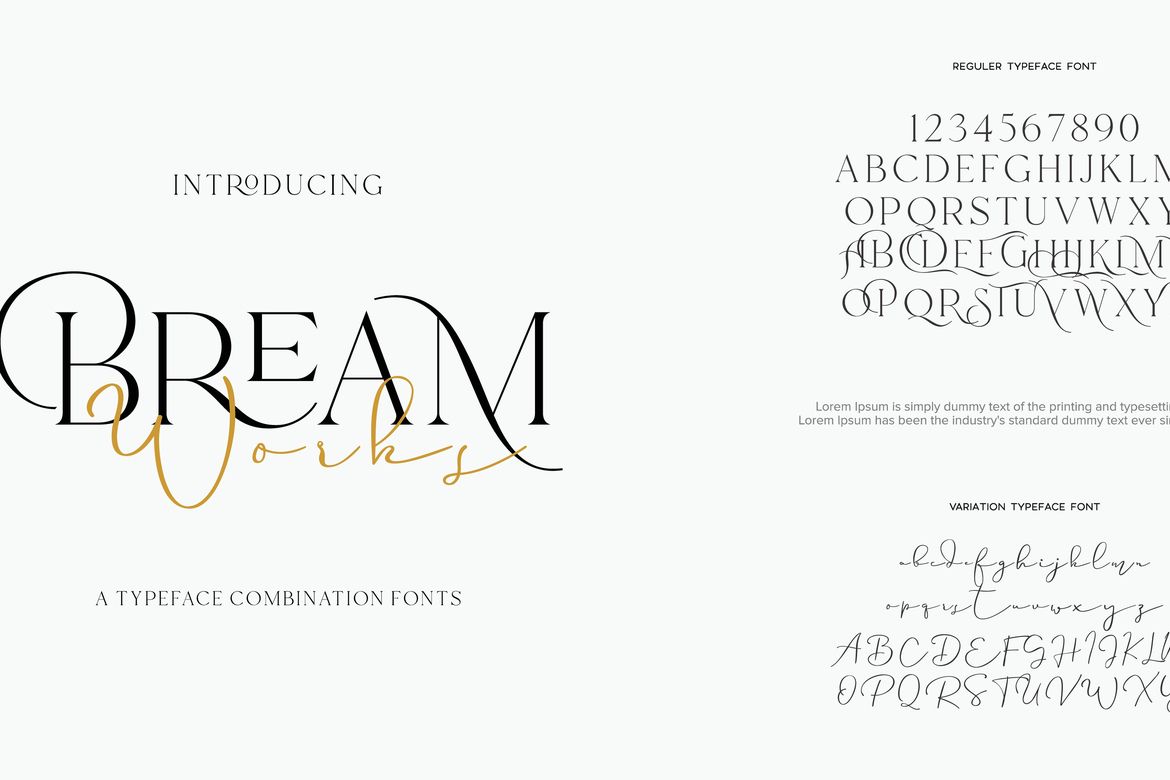
Guida alla differenza tra font e typeface per realizzare uno stampato perfetto
La distinzione potrebbe apparire un po' pignola, ma chiunque abbia come obiettivo la realizzazione di uno stampato perfetto è necessario che conosca la differenza tra font e typeface. Iniziamo dalle basi:
- il font è un insieme di caratteri che condividono la stessa scelta grafica, lo stesso stile
- il typeface è la famiglia di un tipo di carattere
Con il termine typeface ci si riferisce, quindi, a caratteri della stessa tipologia, ma con diverso peso: regular, thin, bold, medium, italic, che corrispondono a regolare, sottile, grassetto, corsivo. Il font rientra, invece, in una famiglia più grande. Il termine deriva dall’antica tecnica tipografica che prevedeva la creazione in metallo dei singoli caratteri (font ha la stessa radice di “fondere”). Si intendono tutti caratteri delle stesse dimensioni, stile e peso che vantano il medesimo design. La scelta dei font può determinare il successo o meno di un progetto editoriale, la forza comunicativa del font viene, infatti, associata alle tipologie di messaggio e alla sua modalità di veicolazione. I font classici, lineari e puliti sono, ad esempio, spesso scelti per le comunicazioni istituzionali.
Nonostante la differenza tra font e typeface dobbiamo specificare che entrambi sono composti da glifi, ovvero tutti i caratteri possibili, come lettere, numeri e caratteri speciali.
Differenza tra font e typeface: serif e sans serif
I typeface possono rientrare in due categorie: serif e sans serif, cioè caratteri “con grazie” o “senza grazie”. I typeface serif sono più tradizionali, hanno piccole appendici alle estremità dei caratteri, le grazie, questo a differenza dei typeface sans serif che ne sono privi. Un esempio di typeface sans serif è l’Helvetica. In linea generale possiamo dire che i serif sono più adatti alla stampa, nel graphic design, invece, i sans serif sono più utilizzati perché rendono meglio sullo schermo.
Come orientarsi tra font e typeface
Per la realizzazione di brochure, riviste, presentazioni aziendali o pubblicità vi sono font più o meno indicati. Come avrai capito la differenza tra font e typeface è molto sottile, anche perché nel linguaggio italiano questi termini vengono talvolta confusi.